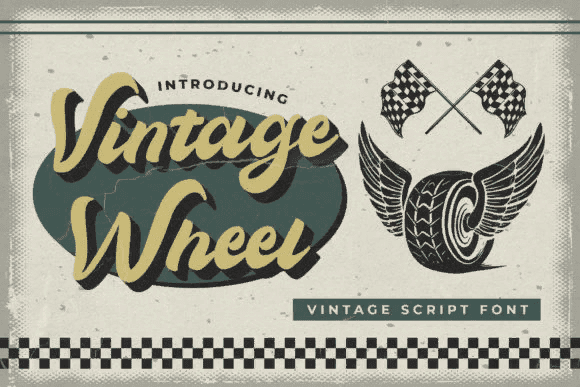
Название: Vintage Wheel Font (2021)
Vintage Wheel - это уникальный винтажный шрифт.
Влюбитесь в его невероятно универсальный стиль и используйте его для создания свадебных приглашений, ретро канцелярских товаров, привлекательных постов в социальных сетях, этикеток, логотипов, веб-страниц, цитат, плакатов, одежды, мастерских и многого другого!